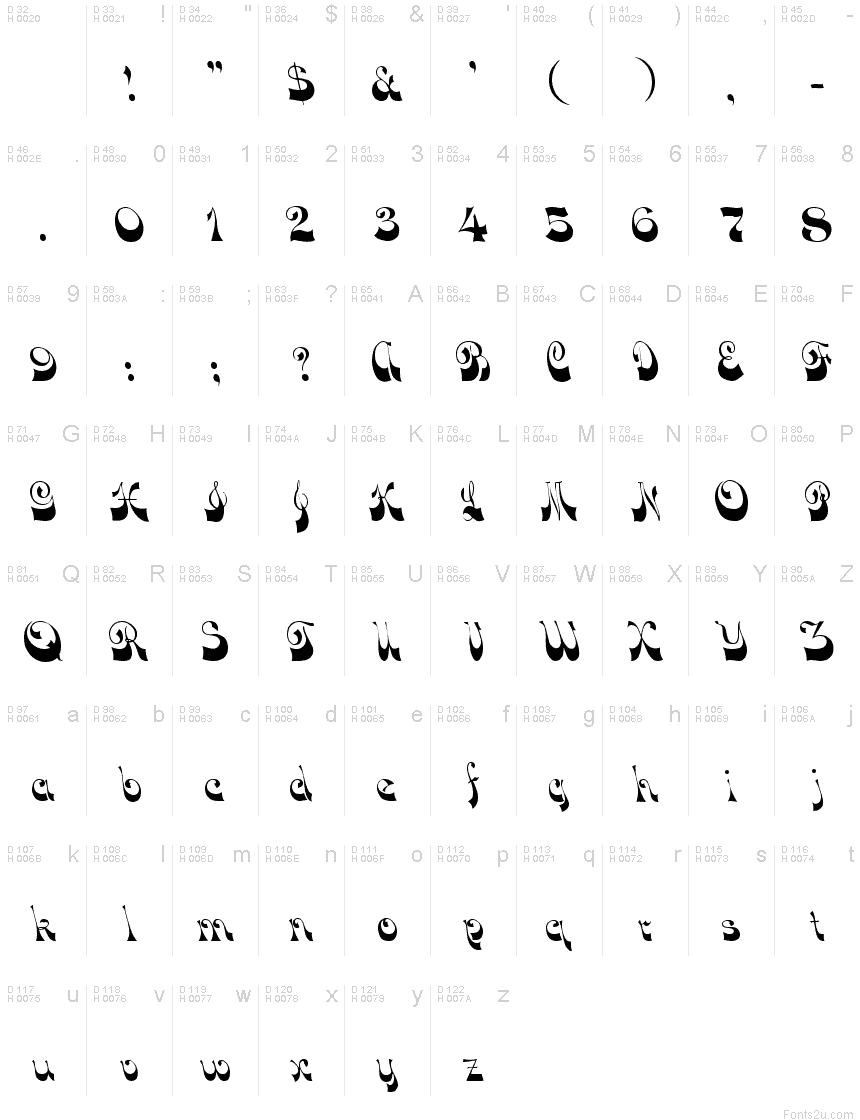
Downwind to darmowy, ozdobny krój pisma, który wygląda, jakby każdą literę porwał nagły podmuch wiatru. Wysokie, atramentowe pociągnięcia rozszerzają się i zwężają w skręcone haczyki i dynamiczne końcówki, nadając słowom poczucie ruchu, dramatyzmu i odrobinę figlarności. W ramach rodziny Downwind ten styl wyróżnia się wyrazistością i teatralnym charakterem, przyciągając wzrok nawet w przeładowanym projekcie.
Dzięki Downwind nagłówki nabierają czarującego, nieco tajemniczego klimatu. Czcionka ta świetnie sprawdzi się na okładkach książek fantasy, gotyckich plakatach, ulotkach na magiczne wydarzenia, grafikach na Halloween, logotypach butików, etykietach na mikstury czy perfumy oraz teatralnych planszach tytułowych. Ten darmowy font najlepiej prezentuje się w większych rozmiarach, gdzie jego krzywizny i zdobienia mogą naprawdę wybrzmieć. Połącz go z prostym bezszeryfowym krojem w tekście głównym, aby pozwolić „wietrznym” literom pozostać w centrum uwagi bez przytłaczania projektu.